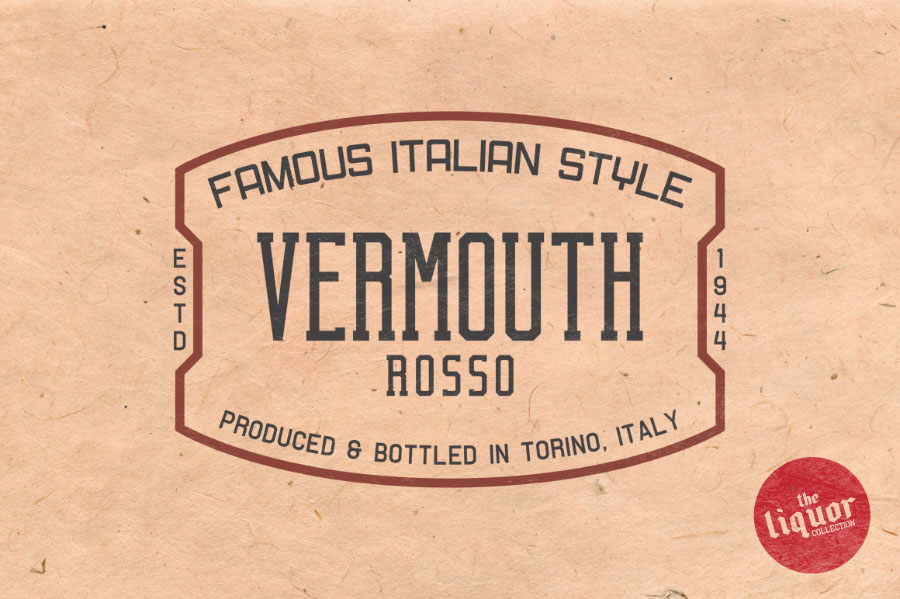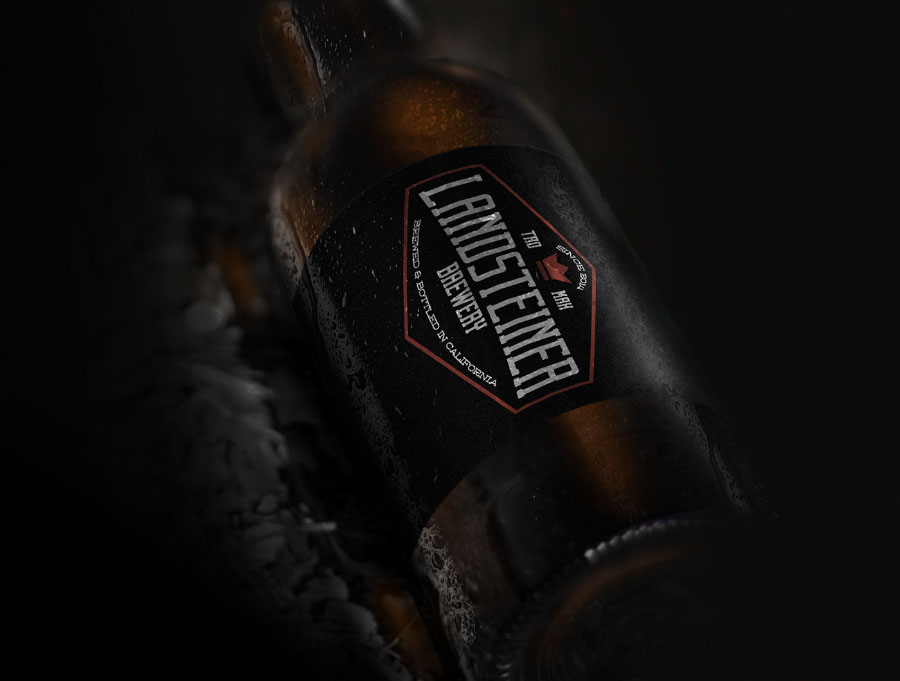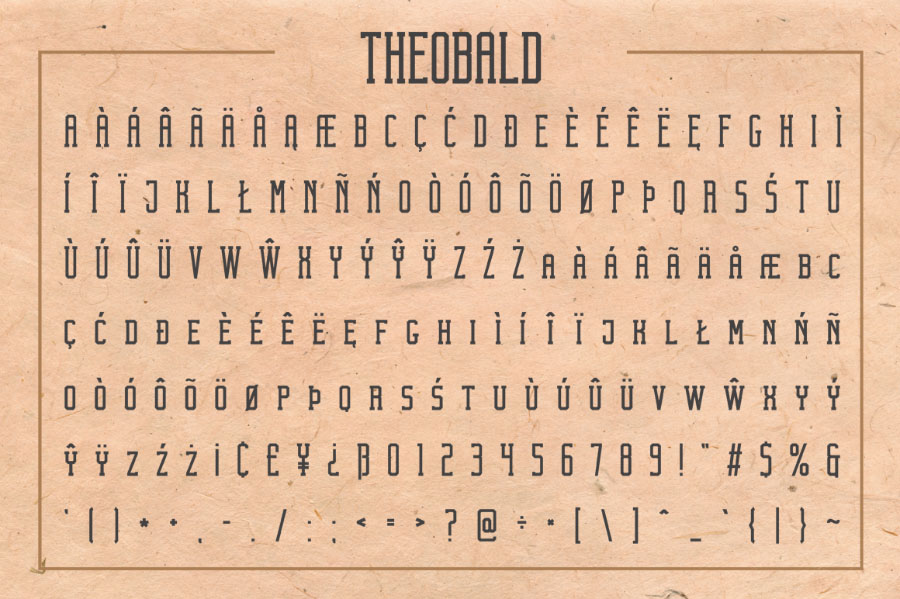
Theobald清理免费字体
Theobald Clean Free Font
Theobald Clean Free Font是一款复古浓缩字体,由老式啤酒标签,海报和广告启发。它也包含多种语言的支持,并且非常适合品牌推广。您可以使用它来制作自己的徽标,品牌,海报,印刷设计等等。所以,现在下载并做一些真棒设计!